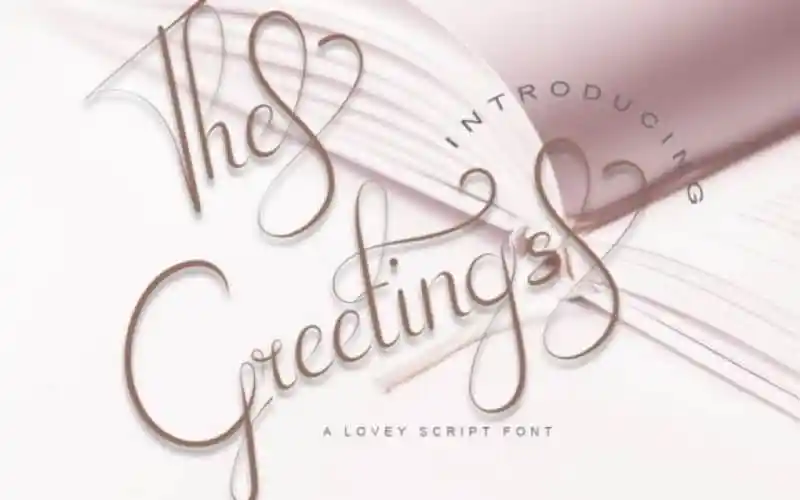
The Greetings Calligraphy Font – Fonte Grátis
The Greetings Calligraphy Font
A fonte The Greetings Calligraphy Font é uma inovação moderna que traz elementos únicos ao mundo das fóntes de script, criada pelo designer IndroTanwijoyo. Esta elegante criação combina um estilo artesanal tipográfico com caracteres decorativos e uma linha base que dança, tornando-a perfeita para uso em convites e cartas de cumprimento, materiais de marca, cartões de negócios, citações, posters e muito mais. É uma escolha ideal para quem busca algo fresco e moderno para dar um toque especial a seus projetos gráficos. Seu design sofisticado se destaca em qualquer aplicação onde deseja transmitir emoção e elegância de maneira única.